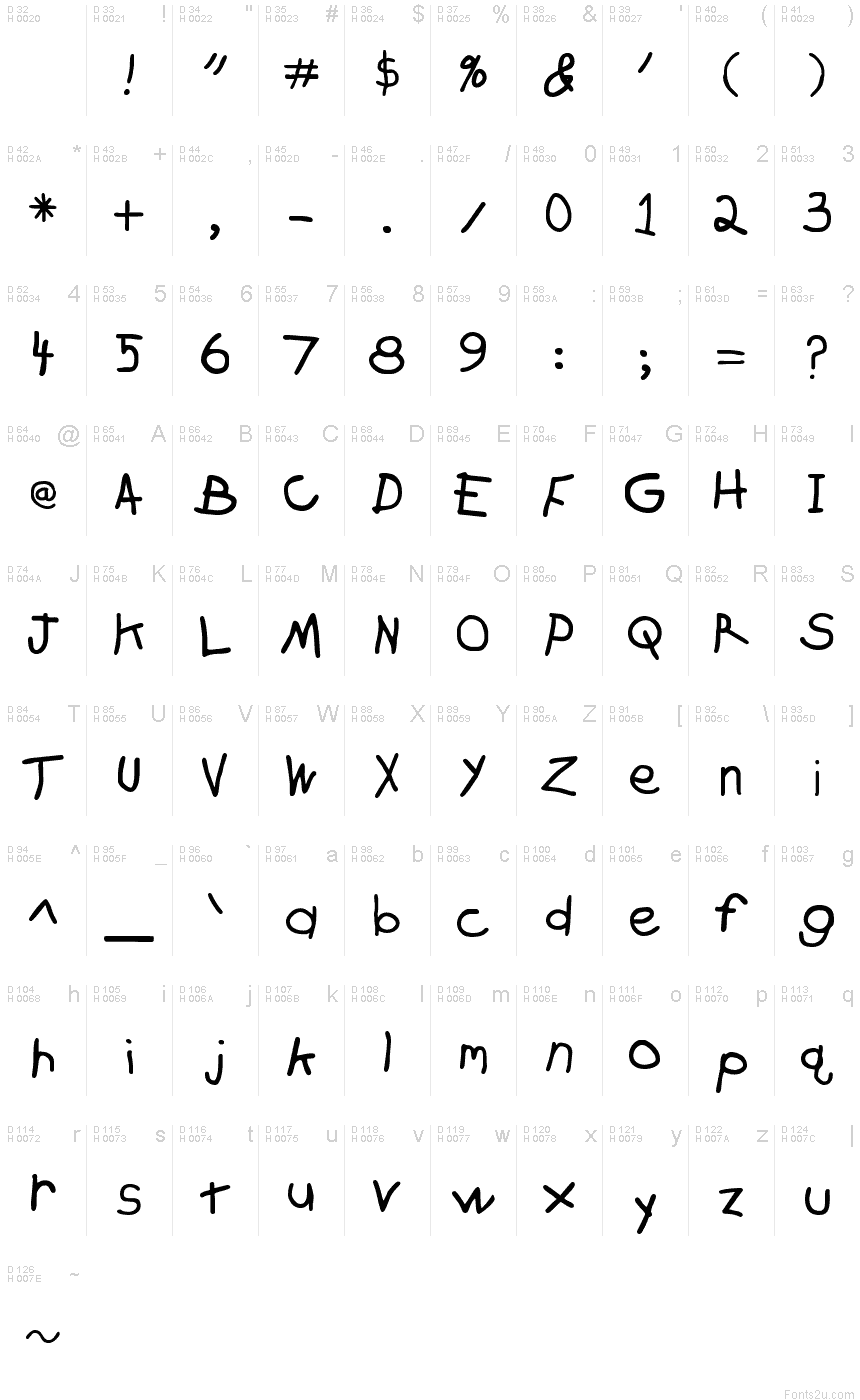
Zachary od Edwarda Leacha je bezplatný font s ručně psaným vzhledem, který má uvolněný, neformální rytmus a jemný retro nádech připomínající fixu. Písmena tvoří měkké, zaoblené tahy, ale díky dlouhým vertikálám a širokým, rozmáchlým křivkám nepůsobí přeslazeně; vypadá spíše jako rychle a sebejistě načrtnutý titulek.
Hodí se na plakáty, obaly ve stylu mixtape, branding kaváren, přáníčka nebo neformální obaly, kde by písmo mělo působit osobně, nikoli vybroušeně. Použijte ho všude tam, kde chcete krátkým slovům, jménům nebo titulkům vtisknout ručně kreslený dojem – nepravidelné spoje a přirozené křivky dodávají písmu lidský rytmus.